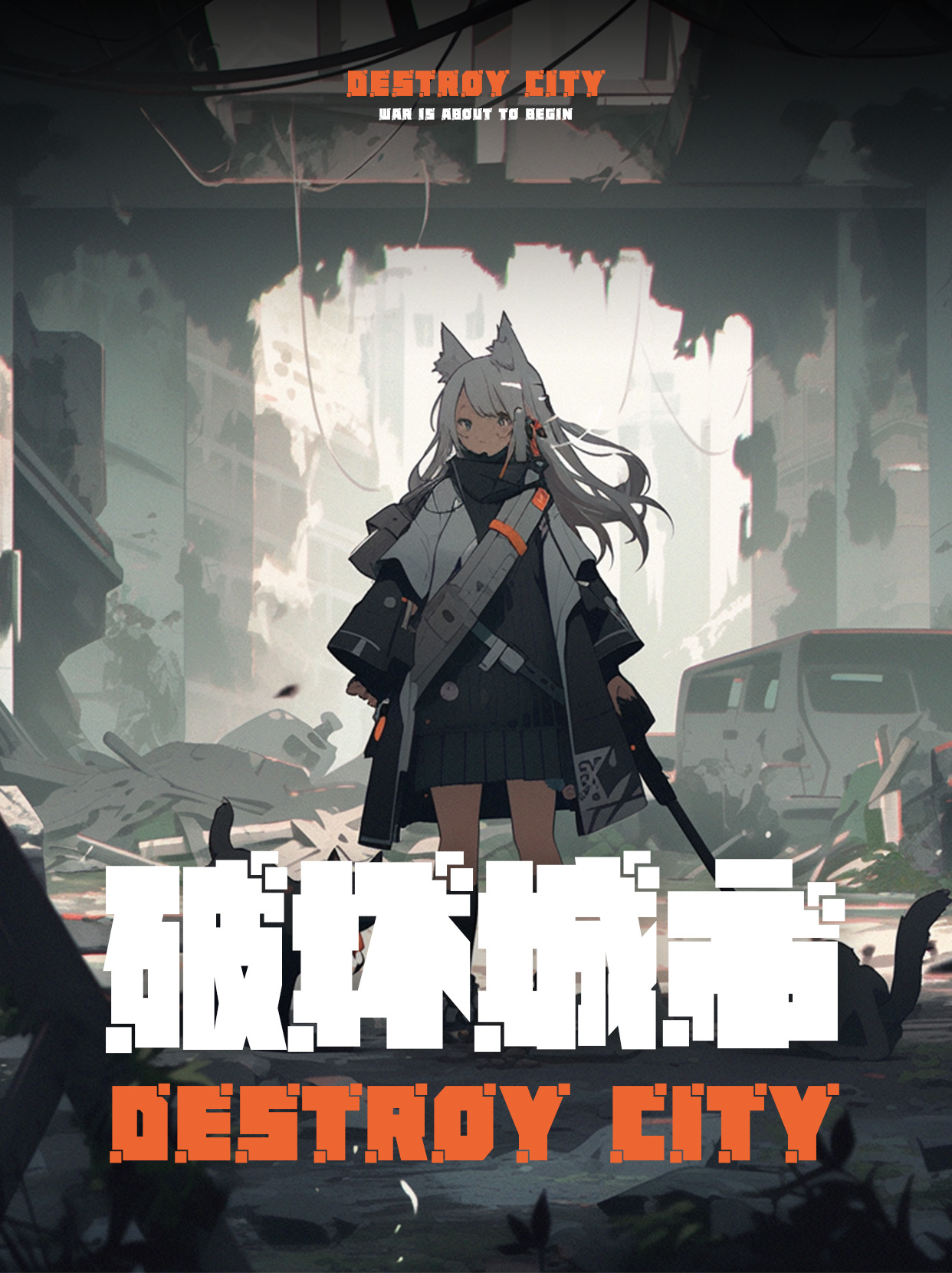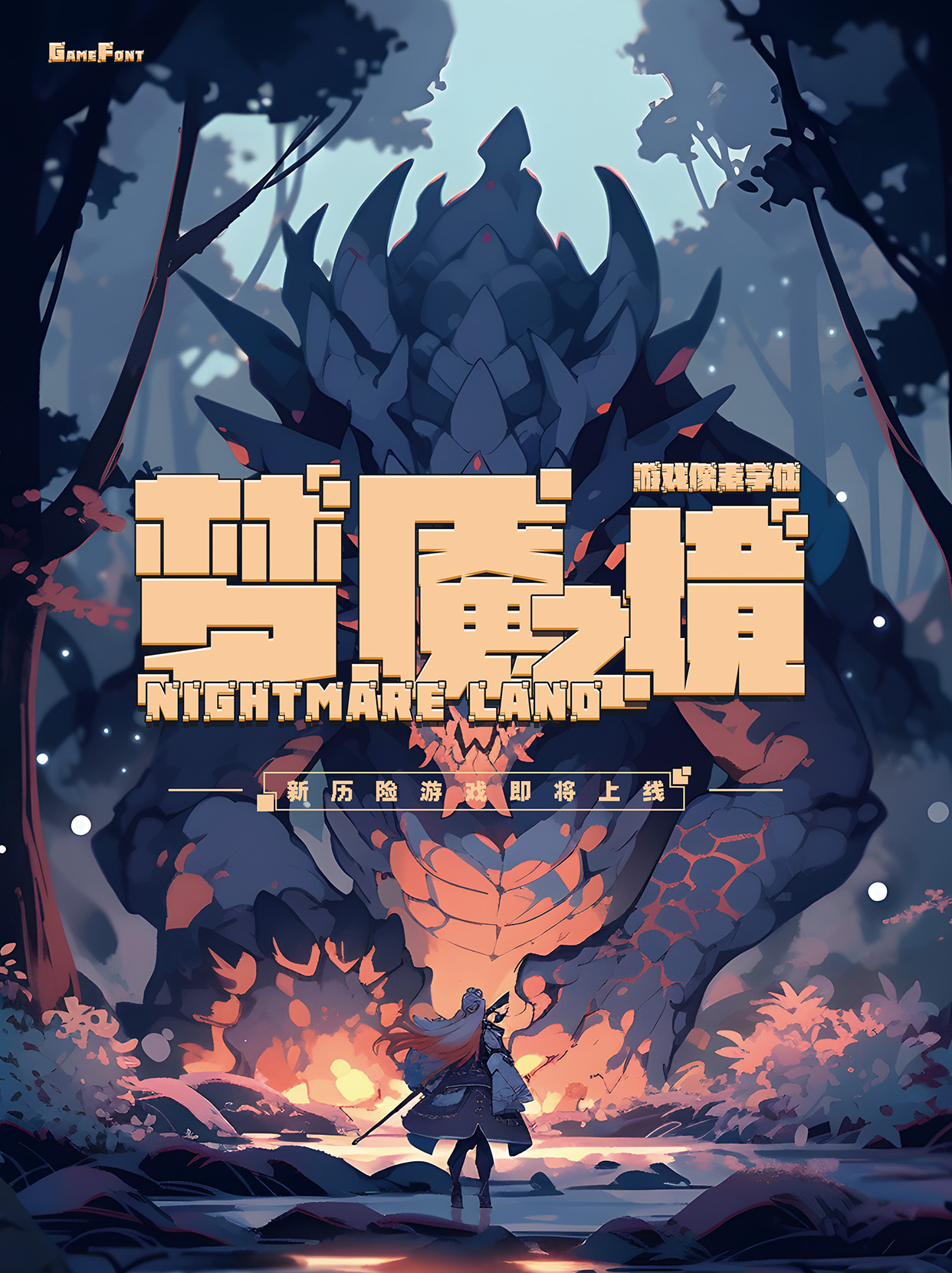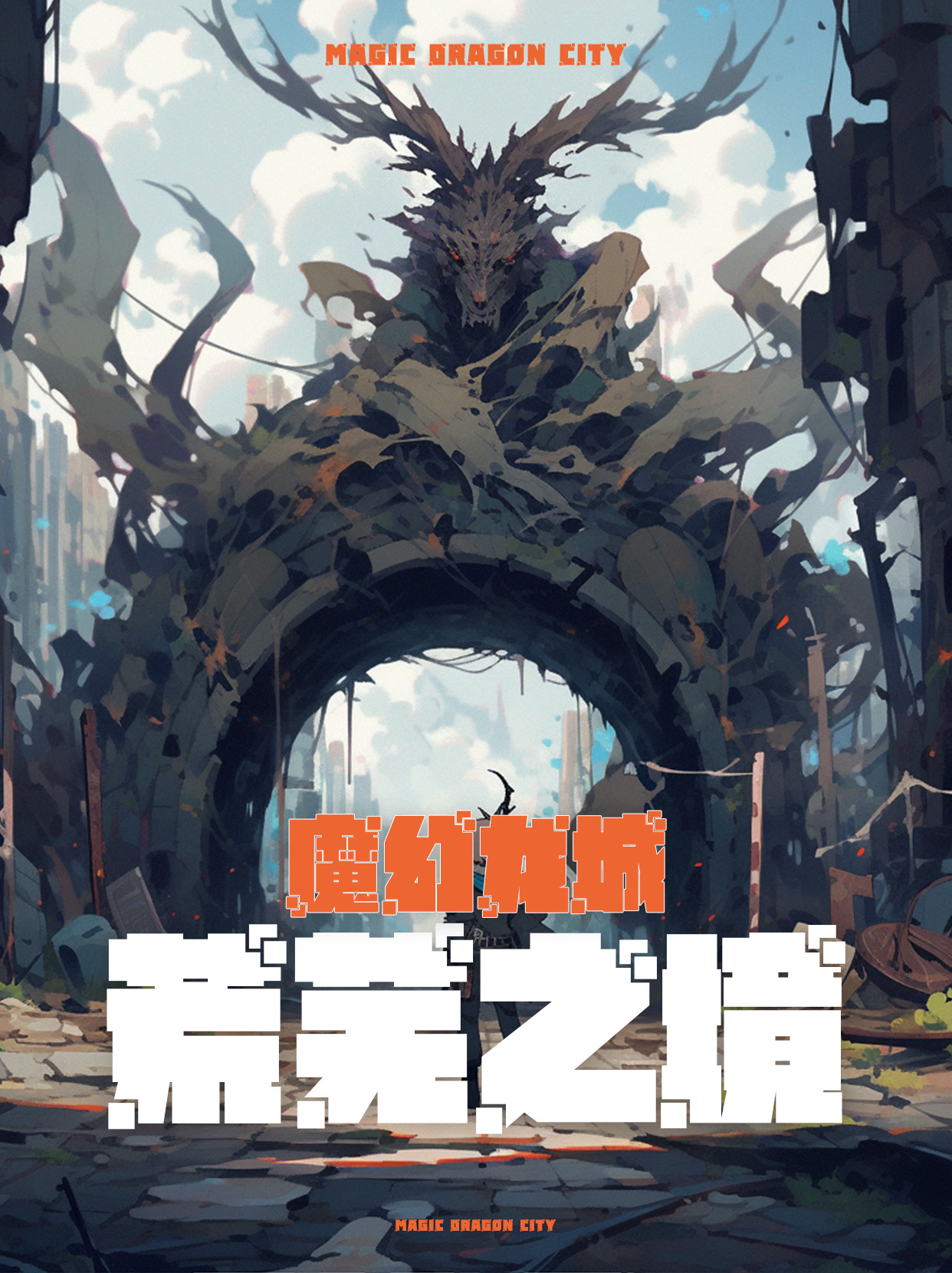
锐字太空夺宝像素简超级黑是一款像素马赛克字体,笔画粗重有力,布白均匀,有很强的方块感和厚重感。笔画横平竖直,灰度均匀,在保证识别度的同时字体左下和右上对角处的部分笔画用像素马赛克拼合代替,奇趣各异,使字体保持整体风格统一的同时又增添趣味性。对于笔画少、内部空间大的字体,加入阶梯特点,更显字体个性与风格。